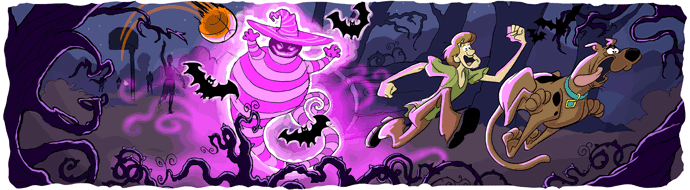
Google's Doodle
เลนนอนจ้ะ  :54:
กดจิ้มแล้วเล่นเพลง Imagine ด้วยแหละ
หายไปซะแล้ว ไม่ได้จิ้มจิ้มเลย เสียดาย  :56:
พยายามจะไปหาจิ้มๆฟังเพลงบ้างแต่เจออันนี้มาแทน  :53:
John Lennon Google Doodle
สุขสันต์วันฮาโลวีน โดย Scooby Doo!
บางอันก็สวยดีนะ
มันอ่านว่ากูเกิลตรงไหนวะ :3005:
Google ต้องใช้จินตนาการมาก  :30:
นั่นแหละเจ๋ง คือไม่ต้องง้อใครแล้วไง จะอ่านออกรึเปล่าเรื่องของมึง :30:
ตรงตัว OO เห็นแล้วนึกถึงโลโก้ห้างแว่น top เจริญแฮะ
เพิ่งเห็นว่ามันเรืองแสงวืบวาบได้ :51:
160ปี ชาตกาล Robert Louis Stevenson ผู้ประพันธ์ Treasure Island :25: